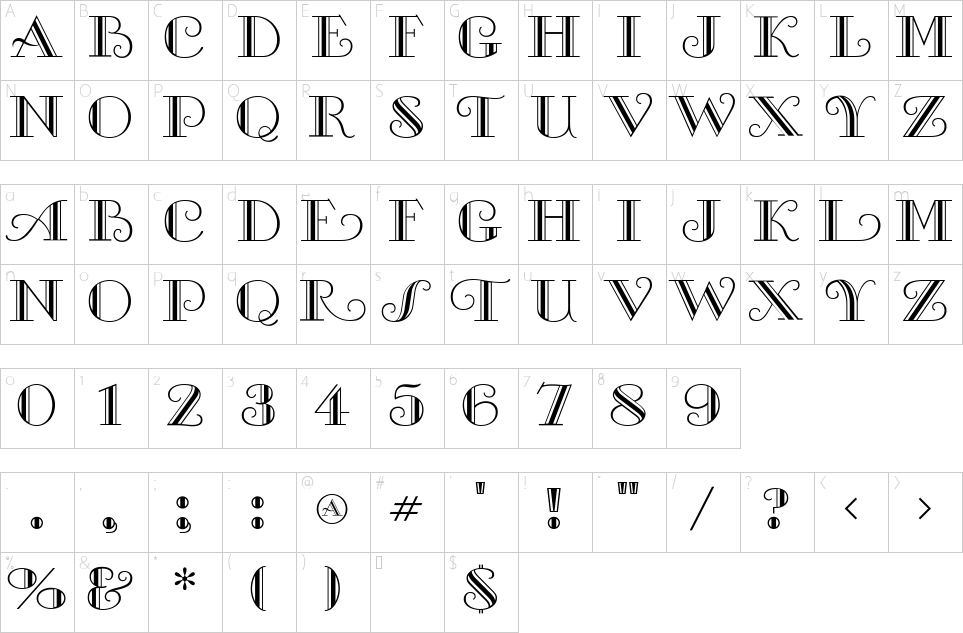
Michelle é uma elegante fonte gráfica que pode ser utilizada tanto em projetos digitais quanto em impressões. Desenvolvida pelo casal Casady & Greene, ela carrega uma versatilidade que se adapta perfeitamente a uma vasta gama de usos, desde design editorial e logotipos até o conteúdo digital. Suas linhas sutilmente curvadas e acentos diferenciados proporcionam um toque de sofisticação sem se tornar abstrato ou difícil de ler. Com o download da Michelle font para ambientes Windows e Mac, você poderá personalizar textos de diversas maneiras, tornando suas criações ainda mais únicas e atraentes. Esta fonte tem sido baixada por 19.403 usuários, evidenciando seu valor e popularidade.